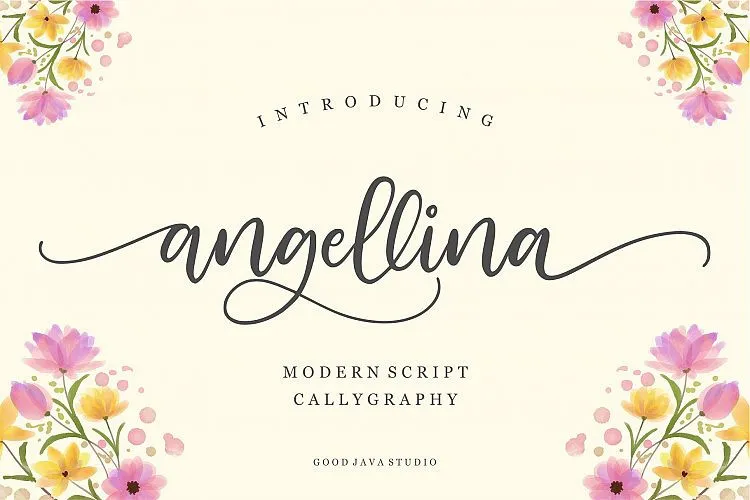
Angellina Script Font – Fonte Grátis
Angellina Script Font
Aqui está uma descrição natural e envolvente para a página de download da font ‘Angellina Script Font’, seguindo as instruções: A Angellina Script Font é um charmoso design do tipo, perfeito para qualquer projeto gráfico. Inspirada em tipos manuscritos modernos, ela oferece uma combinação única de elegância e naturalidade. Ideal tanto para aplicar em logotipos, convites, estacionários ou mesmo em postagens nas redes sociais, Angellina é um recurso valioso para designers buscando algo que seja claramente único e elegante. Sua forma fluida e arredondada permite que você crie texturas de tipo decorativo perfeitas para qualquer projeto. O seu uso em anúncios de produtos ou embalagens, como etiquetas ou rótulos, também é uma ótima opção, especialmente para criar um design personalizado e atraente. Além disso, se você está buscando algo que dê destaque especial à sua fotografia ou criações digitais, Angellina pode ser o elemento perfeito. Essa font é ideal para eventos especiais e, em geral, qualquer situação onde seja necessário destacar a beleza da tipografia. Não importa qual tipo de projeto você está trabalhando, essa font manuscrita moderna terá um impacto positivo no seu design.